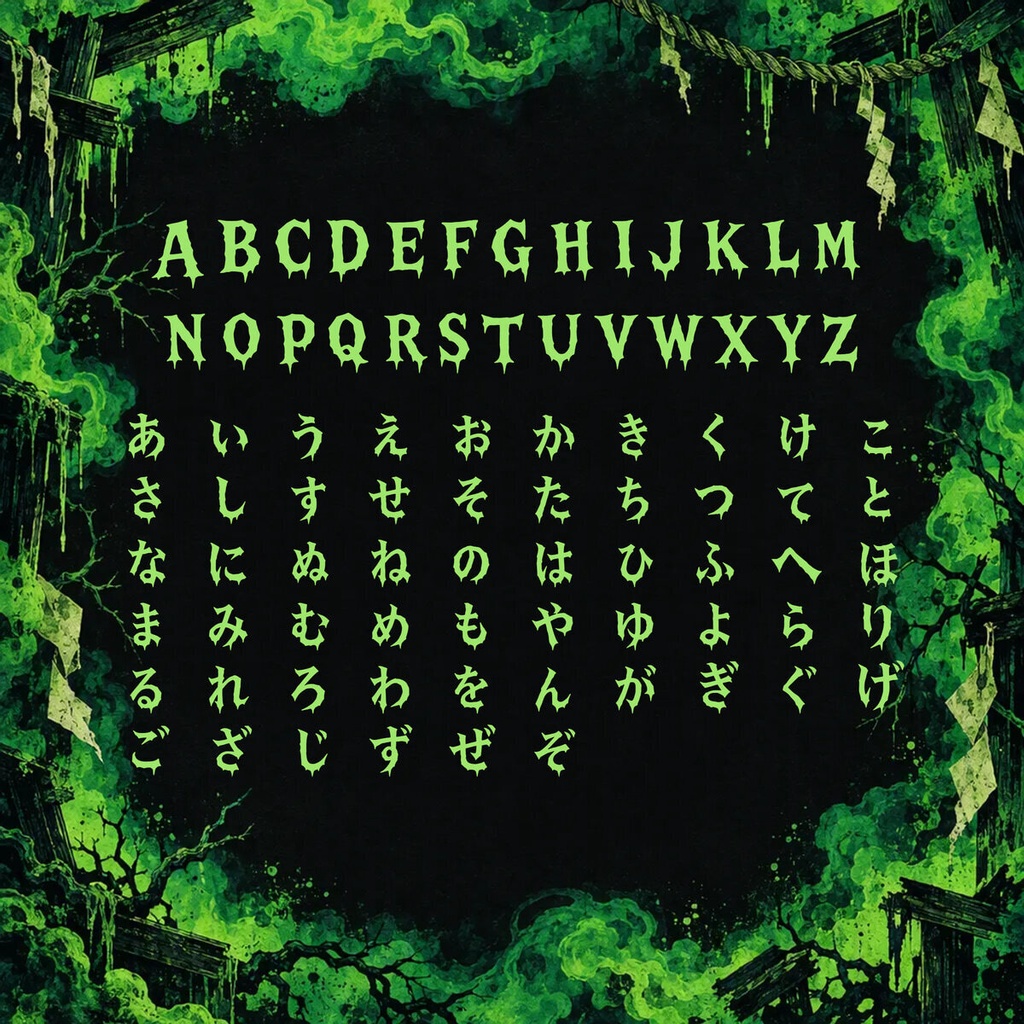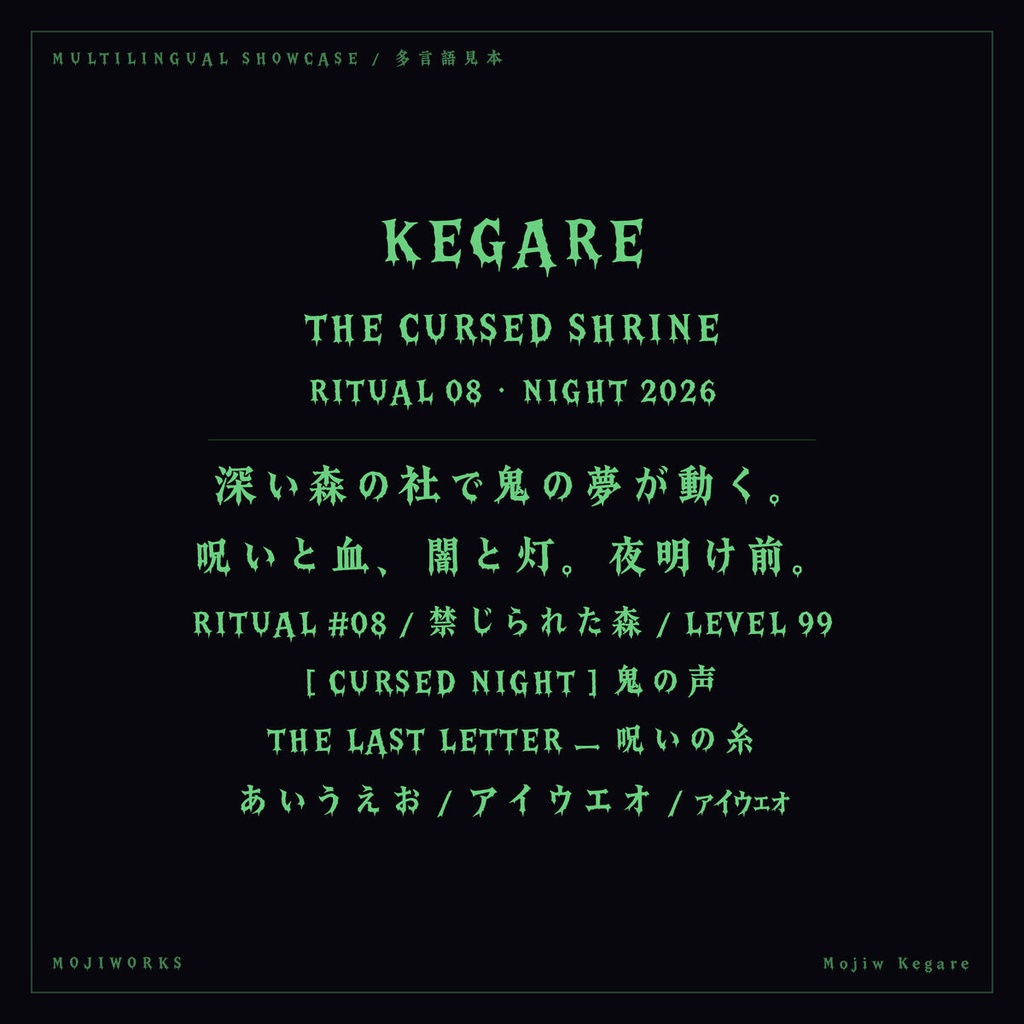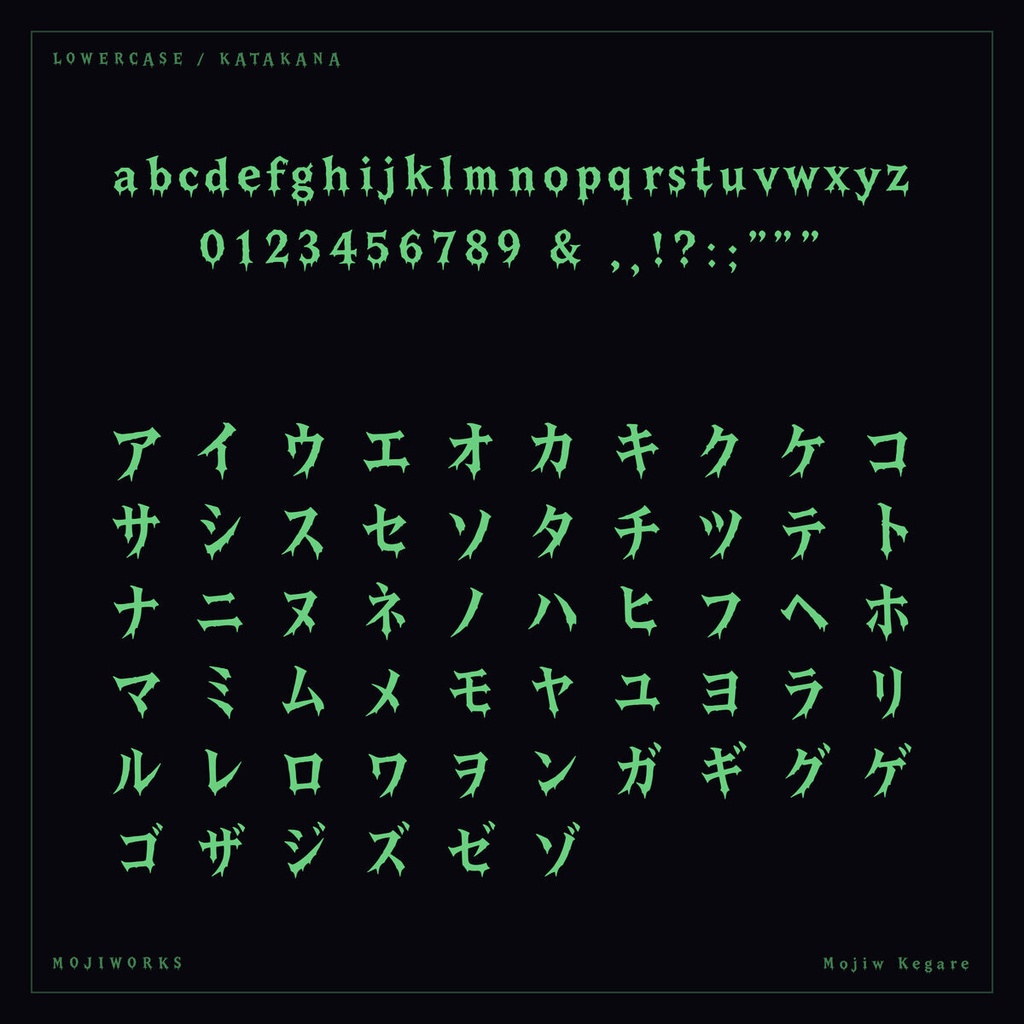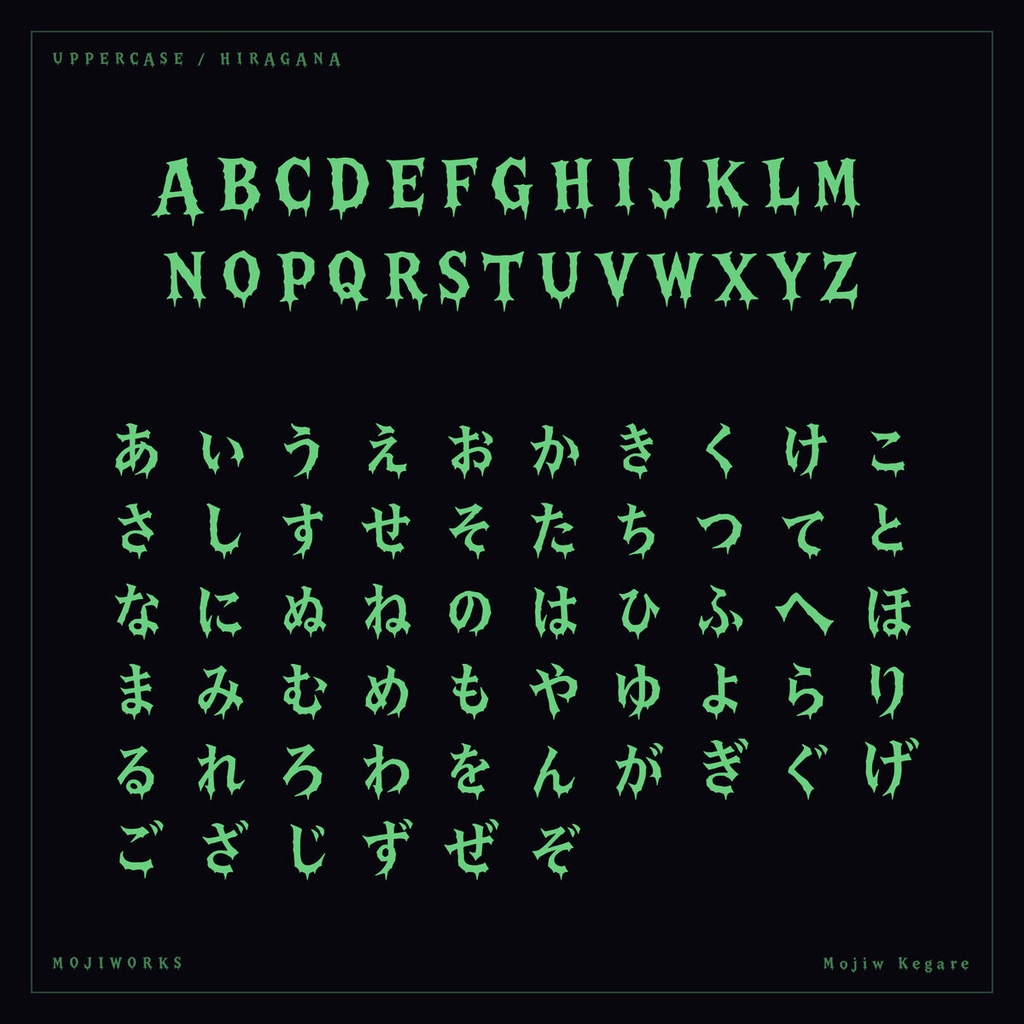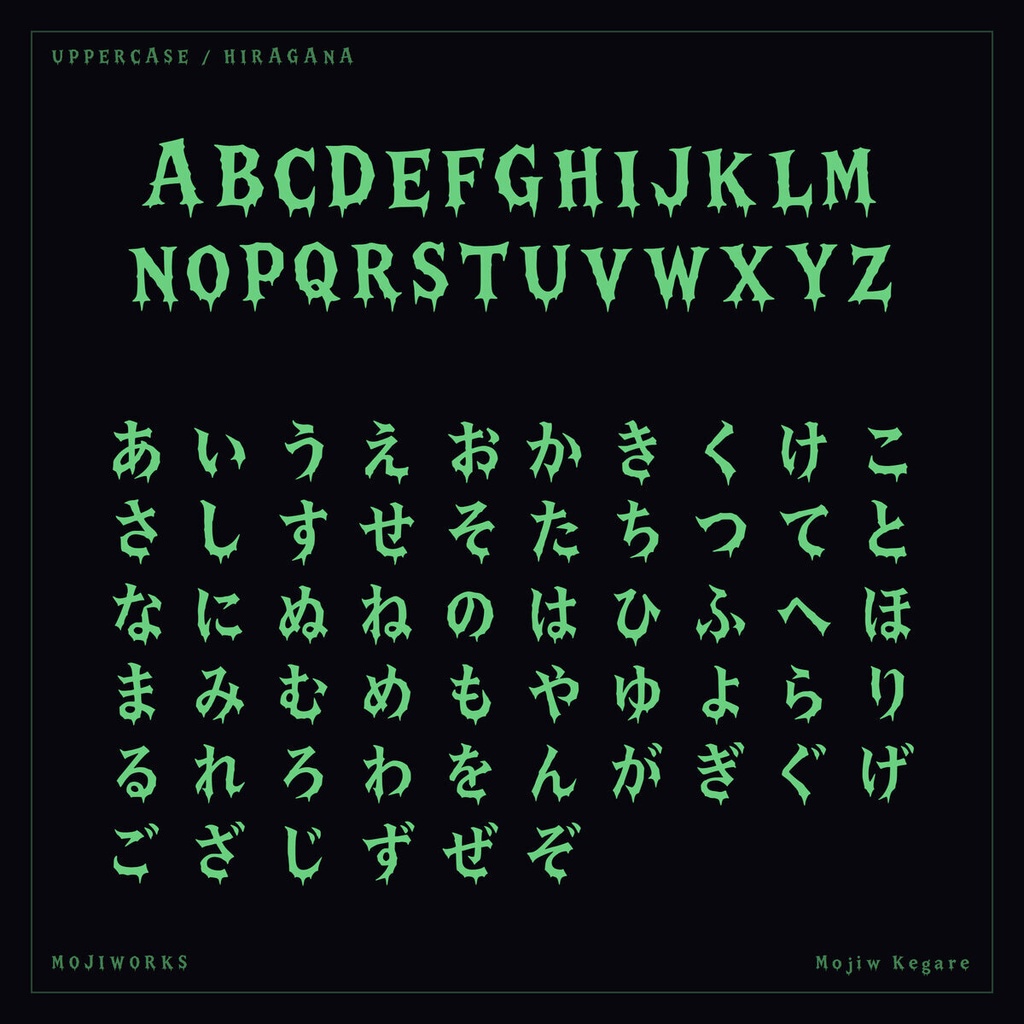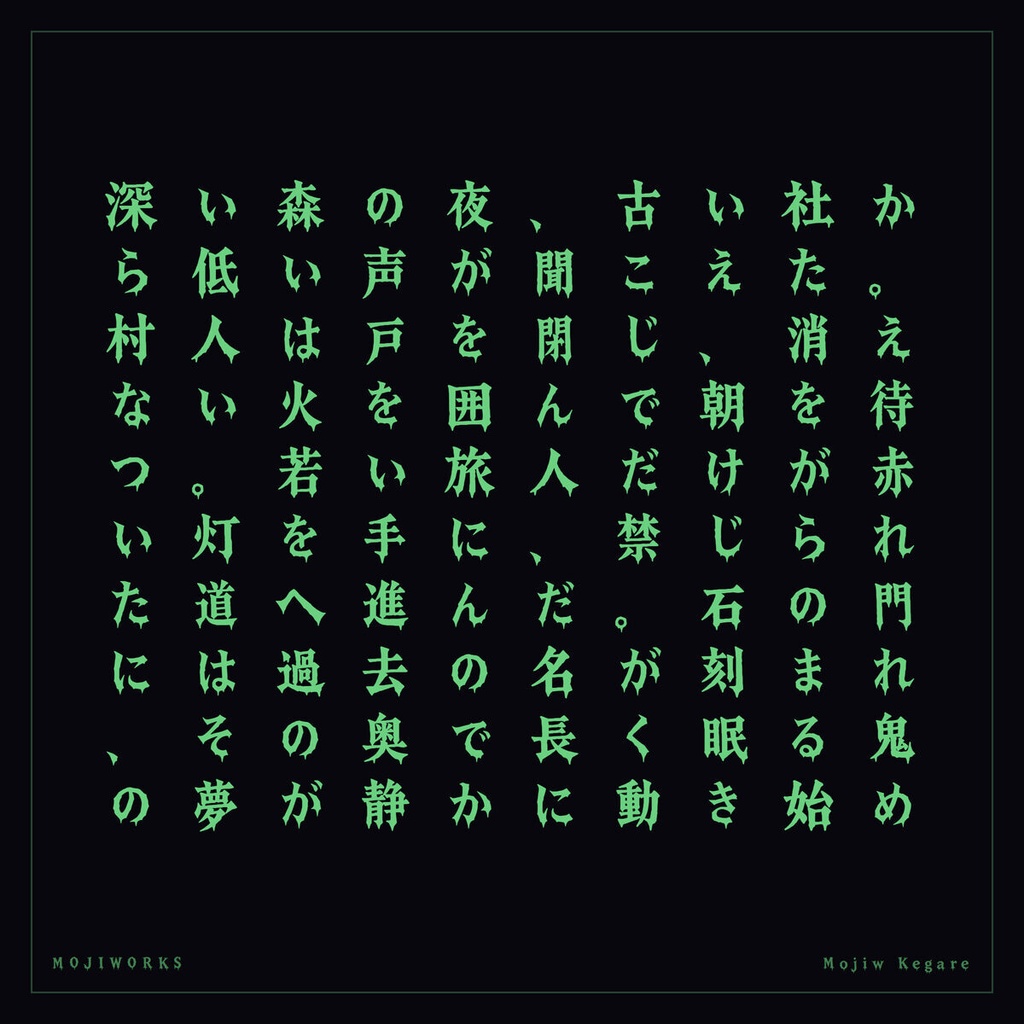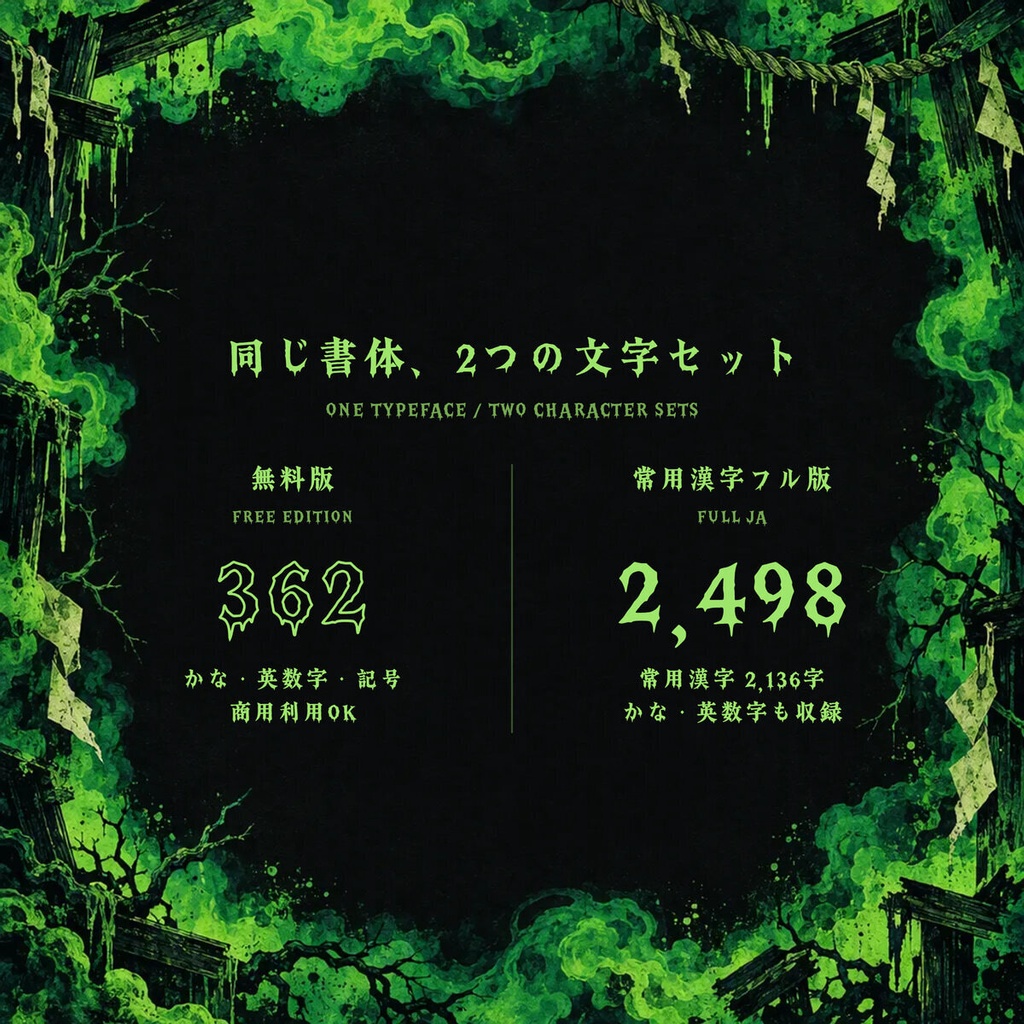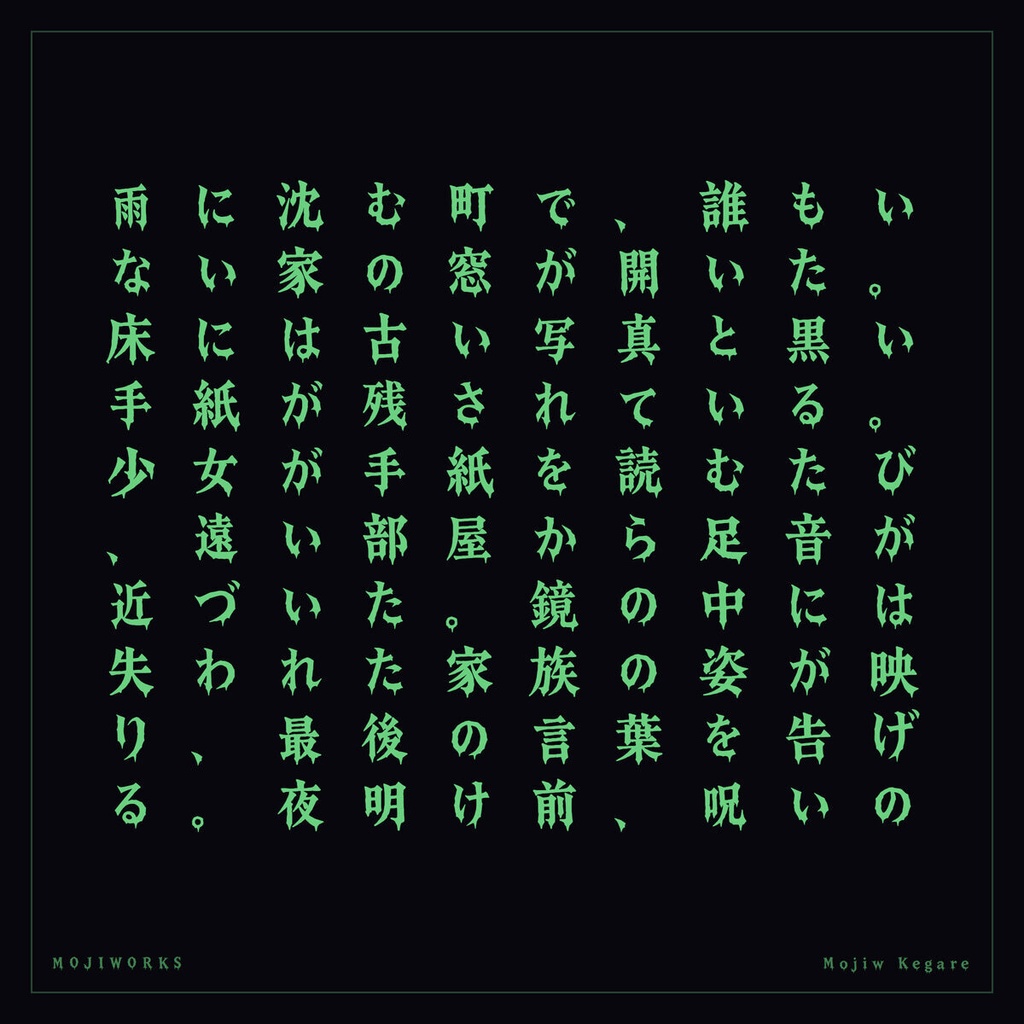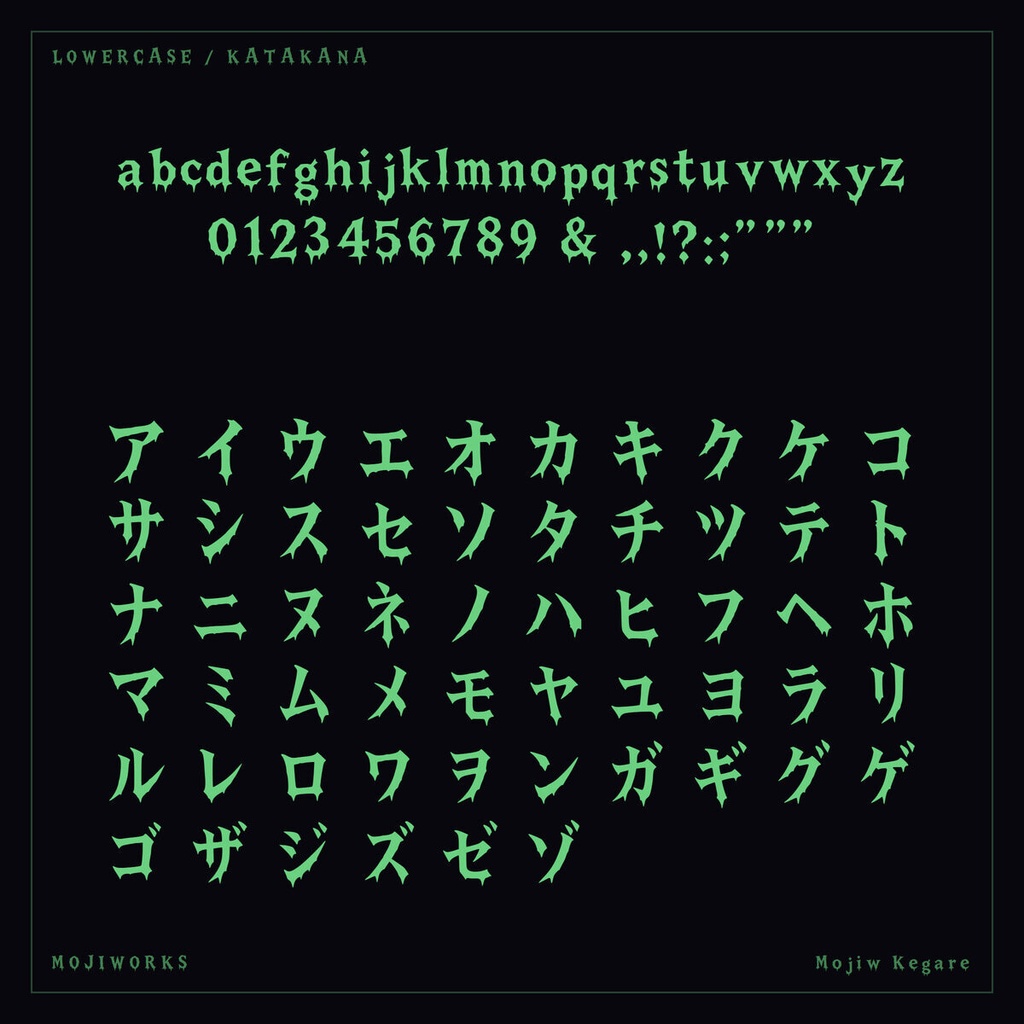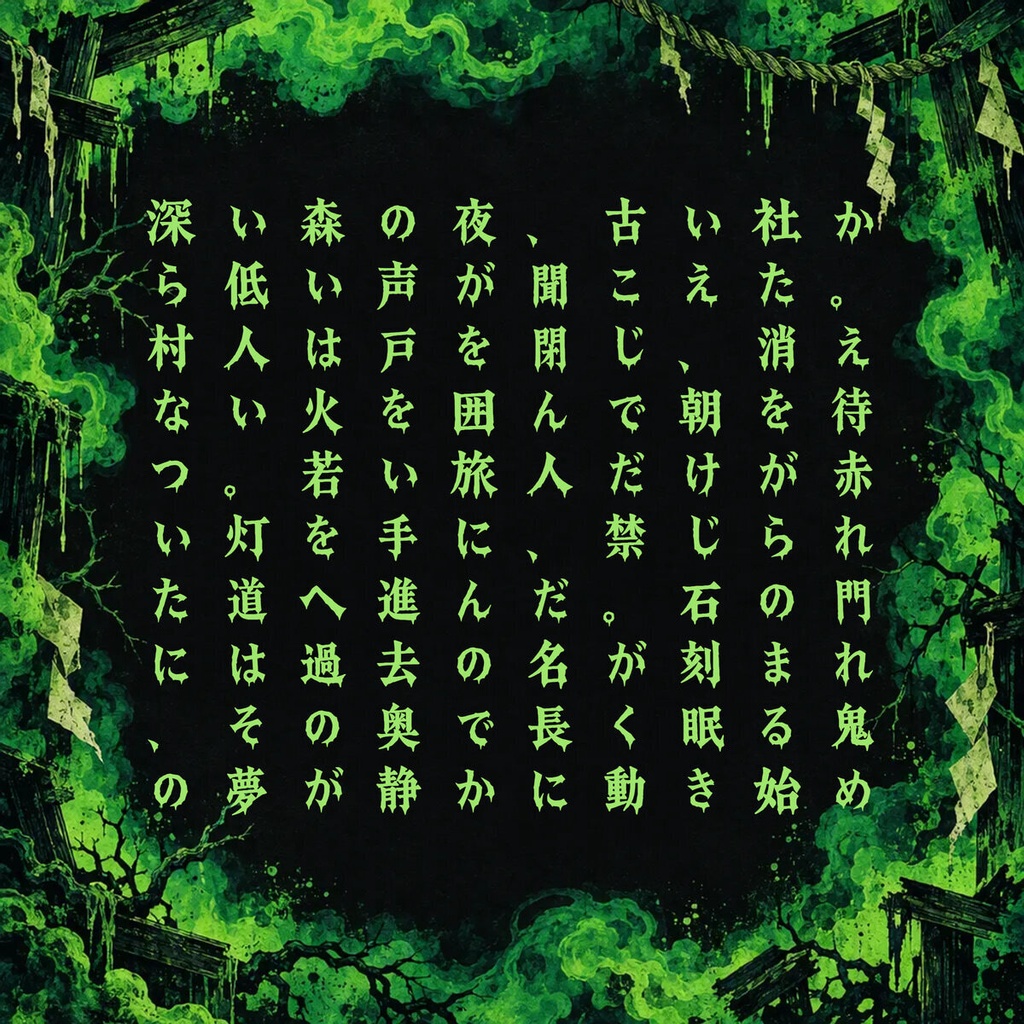
穢れ Kegare【フォント】 — 滲み歪むホラーフォント|常用漢字2,136字
滲み歪む、不気味で穢れたホラー書体です。 An uncanny ritual-horror face with warped, bleeding strokes. 【用途 / Use】 ホラー / 都市伝説 / TRPGシナリオ表紙 / サイケ For horror, urban legends, TRPG covers, and psychedelic designs. 【常用漢字フル版 / Joyo Complete】 常用漢字2,136字を完全収録し、ラテン文字・ひらがな・カタカナ・記号を含む全2,437文字を収録しています。半角カナは収録していません。 Includes all 2,136 Joyo kanji and 2,437 characters total, including Latin, hiragana, katakana, and punctuation. Half-width kana are not included. 2437文字 / characters 【関連する収録版 / Other Edition】 ラテン文字・かな・記号を収録したスタンダード版もあります。 The Standard edition includes Latin, kana, and punctuation. ▶ スタンダード版 / Standard: https://mojiworks.booth.pm/items/8826751 【フォント仕様 / Specification】 バージョン / Version: 1.0.1 形式 / Format: TrueType (.ttf), Web (.woff2) 対応環境 / Platform: Windows, macOS, web browsers 収録字一覧 / Character list: CHARSET.txt 同梱 / Included: font files, README, LICENSE, character list, portfolio PDF, product previews. 【利用規約 / License Summary】 個人・商用利用可。1ライセンスは購入者1名に適用されます。 Personal and commercial use is permitted. One license covers one purchaser. 印刷・動画・ロゴ・グッズ等の静的成果物、および購入者が運営するサイトでの同梱WOFF2の利用が可能です。 Static output such as print, video, logos, and merchandise is permitted. The bundled WOFF2 may be used on a website owned or operated by the purchaser. ゲーム・アプリへの組み込みは、利用者が生のフォントを抽出できない形式に限ります。生のフォントを同梱する場合は別途ライセンスをご相談ください。 Game/app embedding requires protection against extraction of the raw font. Contact us for a separate runtime-embedding license when shipping raw font files. 標準ライセンスは1製品・1サイトあたり年間約100,000ユーザーまで。従業員50名超の組織を含む大規模利用は要相談。 Standard coverage is approximately 100,000 users per product/site/year. Larger use and organizations with more than 50 employees require an extended license. フォント本体の再配布・販売・貸与・変換・グリフ抽出・派生フォント制作・生成AI学習やスタイル参照は禁止です。 Redistribution, resale, lending, conversion, glyph extraction, derivative fonts, and generative-AI training or style reference are prohibited. 完全な利用条件は同梱の LICENSE.txt / LICENSE.jp.txt をご確認ください。 The bundled license files are authoritative; consult them for the complete terms. 【ほかのフォント・カスタム制作 / More Fonts and Custom Work】 フォント一覧、オーダーメイド書体、文字追加、拡張ライセンスのご相談はこちら。 Browse our catalog or contact us for custom typefaces, added characters, and extended licenses. https://mojiworks.booth.pm/